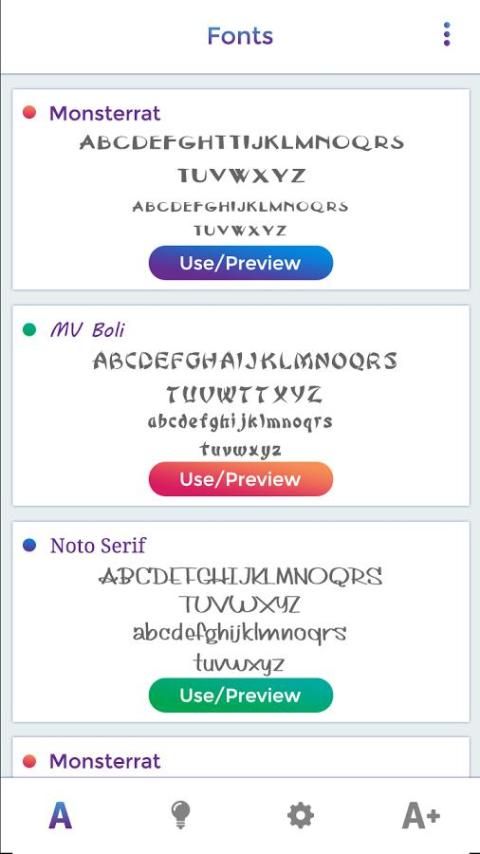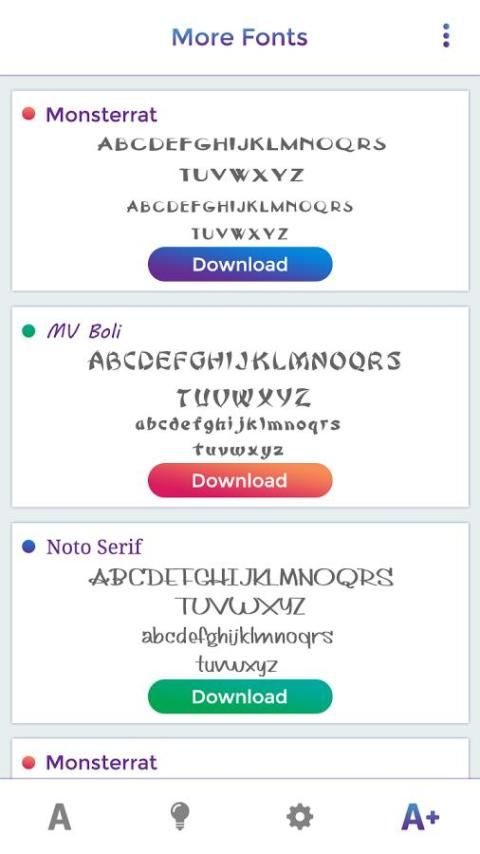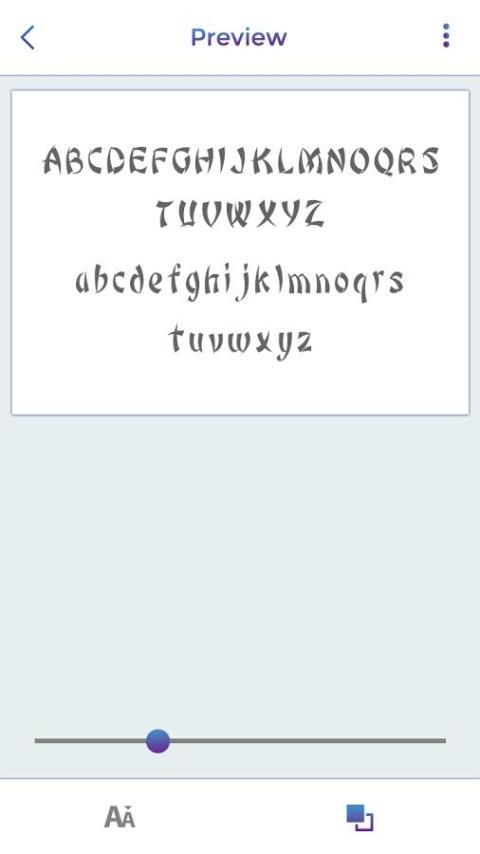
Zawgyi احد نمط الخط
Zawgyi احد نمط الخط التطبيق مع أحدث وأفضل الميزات.
مع Zawgyi احد نمط الخط التطبيق يمكنك تغيير نمط الخط الخاص بك مع مختلف الخطوط الأنيقة.
Zawgyi احد نمط الخط هو مدير الخط فريدة من نوعها لأجهزة الروبوت. Zawgyi نمط واحد الخط توفير عدد من الخطوط الأنيقة، مضحك، بارد، لطيف، Zawgyi احد الخ .. Zawgyi احد نمط الخط سهلة الاستخدام، ومعاينة التفاصيل الخطوط، وتحميل واستخدامها، ثم سيتم تغيير جميع الخطوط النظام.
الميزات الرئيسية لZawgyi احد نمط الخط
1. أرقام من الخطوط باردة ومضحك.
4. دعم معظم اللغات.